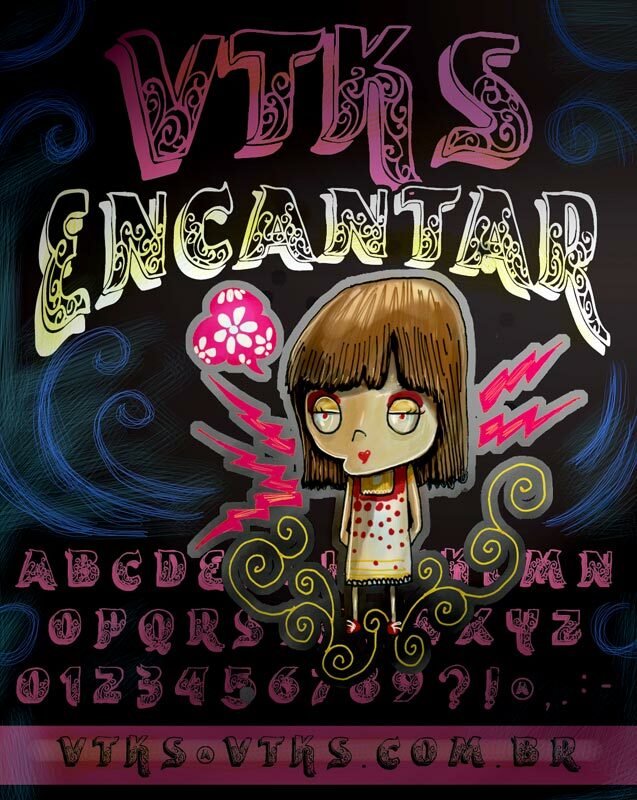
Vtks Encantar von Douglas Vitkauskas ist eine kostenlose, ornamentale Display-Schrift, die an Märchenbücher erinnert. Die Großbuchstaben winden sich in blattartigen, rankenden Schnörkeln. Die Buchstaben wirken handgezeichnet und theatralisch; sie kombinieren kräftige Silhouetten mit tiefen Schatten und geschnitzten, folkloristischen Details, was der Schrift eine leicht verzauberte Stimmung wie auf alten Plakaten verleiht.
Sie passt perfekt zu Buchcovern, Fantasy-Titeln, Veranstaltungspostern, Verpackungsdesign und Café-Brandings, bei denen ein dekorativer Headline-Font ohne zusätzliche Illustrationen auskommt. Verwenden Sie sie auch für kurze Titel, Monogramme oder Initialen, da die Buchstaben bereits ihre eigene Ornamentik und dramatische Textur mitbringen.